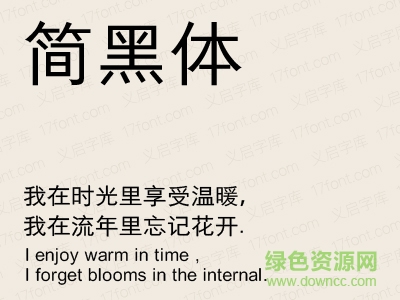
簡黑體,即簡約而不簡單,線條收筆處多以喇叭狀收尾,結(jié)構(gòu)經(jīng)典內(nèi)斂外擴(kuò)重心微向上移,章法明朗流暢。 簡黑體,端莊簡約,筆畫上處理精致得當(dāng)。結(jié)構(gòu)上分配塊面合理,字與字間的距離分配閱讀舒適爽朗。尤其在手機(jī)等移動(dòng)小屏幕上顯示更是簡約極致的體現(xiàn)線條美。